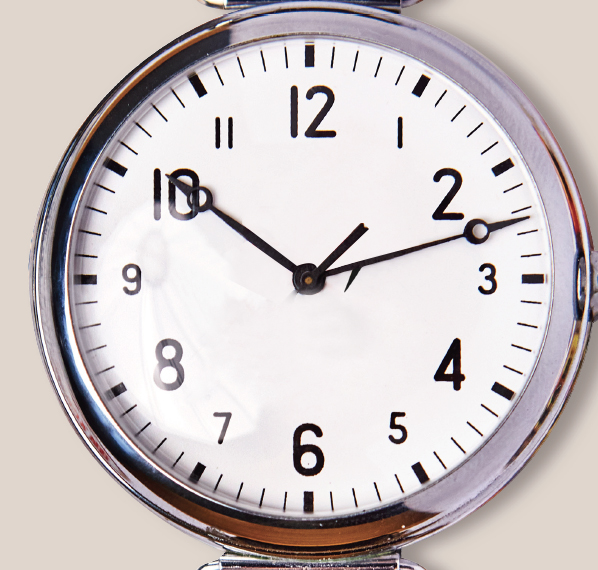
숫자 폰트 뭔지 아시는 고수분 계실가요?
이 숫자 폰트 뭔지 아시는분 있을가요?
마이폰트나 다폰트 찾아도 안나오네요 ㅠㅠ
러시아 시계로 알고있는데 러시아 폰트로 찾아봐야하는걸가요?
비슷한거라도 아시는 고수분 계실가요? ㅠ
마이폰트나 다폰트 찾아도 안나오네요 ㅠㅠ
러시아 시계로 알고있는데 러시아 폰트로 찾아봐야하는걸가요?
비슷한거라도 아시는 고수분 계실가요? ㅠ
이 시계에서만 사용되고 폰트로는 출시가 안되지 않았을까 조심스럽게 생각해봅니다.. 그나마 찾아보니 Sofia pro Soft가 제일 비슷한 점이 많은 것 같아요..
1에 꺾임이 들어가 있지만 제일 비슷한 폰트로 격동굴림2 추천 드립니다. 형태가 비슷해요~!